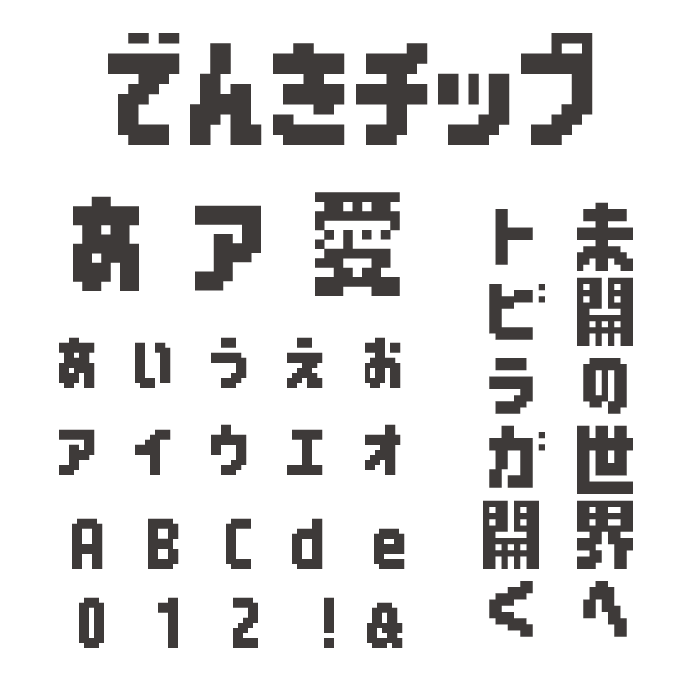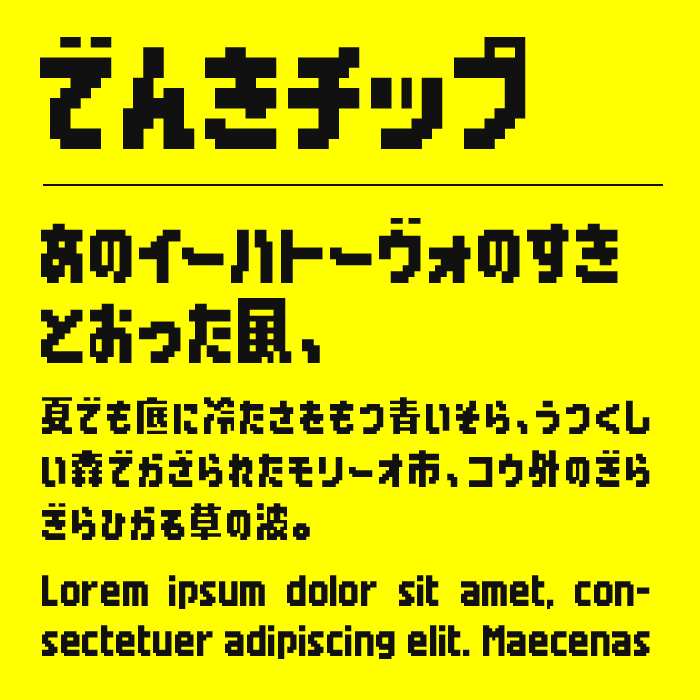
でんきチップは、昔の携帯ゲーム機や初期のパソコン画面を思わせる、レトロ感たっぷりの太めなピクセルフォントです。
細かなドットで構成された文字はどこか機械的でありながら、手作業のような温かみも感じさせてくれるデザインです。無駄を削ぎ落としたシンプルな形状が心地よく、懐かしいデジタル文化の空気をそのまま閉じ込めたようなフォントです。
ゲーム実況風のサムネイルやレトロポップなデザイン、8bit風のビジュアルなどと相性が良く、小さな文字でも独特の存在感を発揮します。
単純なドット文字ではなく、少しだけクセを残した造形が印象的で、見れば見るほど愛着が湧いてきます。レトロゲーム好きの心をくすぐる魅力を持ったフォントです。
収録文字は、漢字・ひらがな・カタカナ・アルファベット・数字・記号が収録。